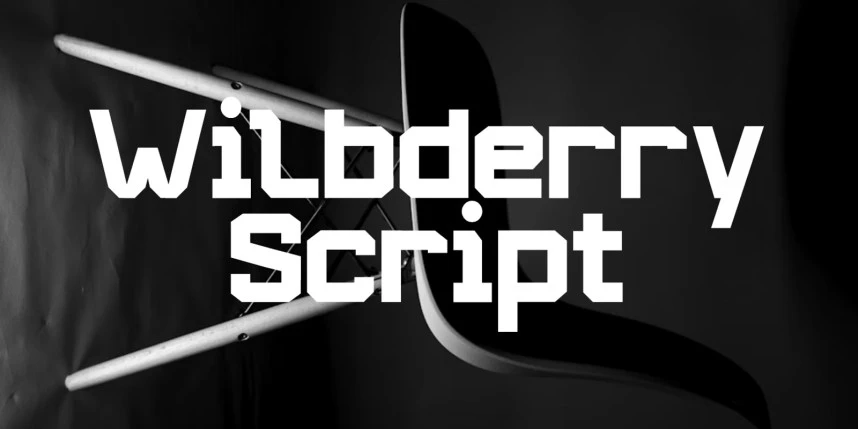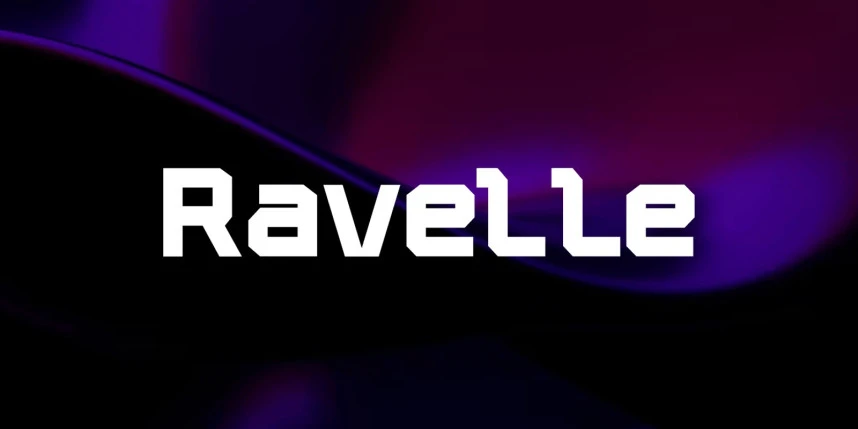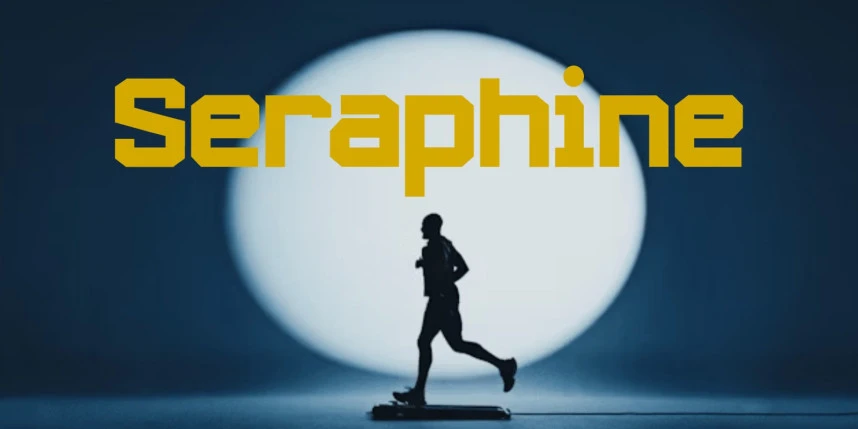
Frontally Font
Frontally Font, güçlü ve kendinden emin bir yazı tipi olup ilk izlenimi güçlendirmek üzere tasarlanmıştır. Temiz hatlara, sağlam yapıya ve çağdaş stile sahip olan bu yazı tipi, netlik, etki ve modern bir zarafetin dokunuşunu talep eden projeler için mükemmeldir.
Frontally Font, güçlü ve kendinden emin bir yazı tipidir; güçlü bir ilk izlenim bırakmak üzere tasarlanmıştır. Temiz hatlar, sağlam yapı ve çağdaş stil ile bu yazı tipi, netlik, etki ve modern zarafetin bir dokunuşunu talep eden projeler için mükemmeldir.